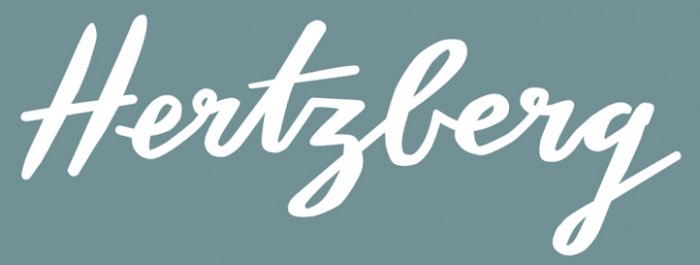
Suche Schreibschrift
Suche die beiden Schriften in den angehängten Bildern!
Hertzberg wird wegen der unterschiedlichen e und r handgezeichnet sein.
Retro wird wegen der unterschiedlichen Anschlüsse ebenfalls handgezeichnet sein.
Hertzberg wird wegen der unterschiedlichen e und r handgezeichnet sein.
Die hässliche t-z-Verbindung, die man handschriftlich wohl kaum so ausführen würde, lässt mich allerdings ein wenig stutzen. :-?
EDIT: Und für die hässliche H-e-Nichtverbindung gilt das ja auch. Vielleicht isses doch ein (stellenweise aber doch schlecht gemachter) Font mit Alternativ-Glyphen für e und r?